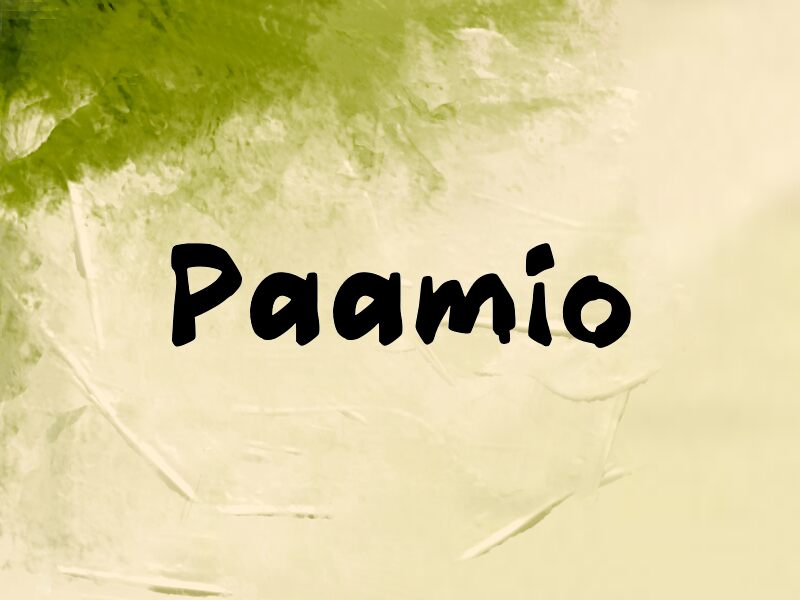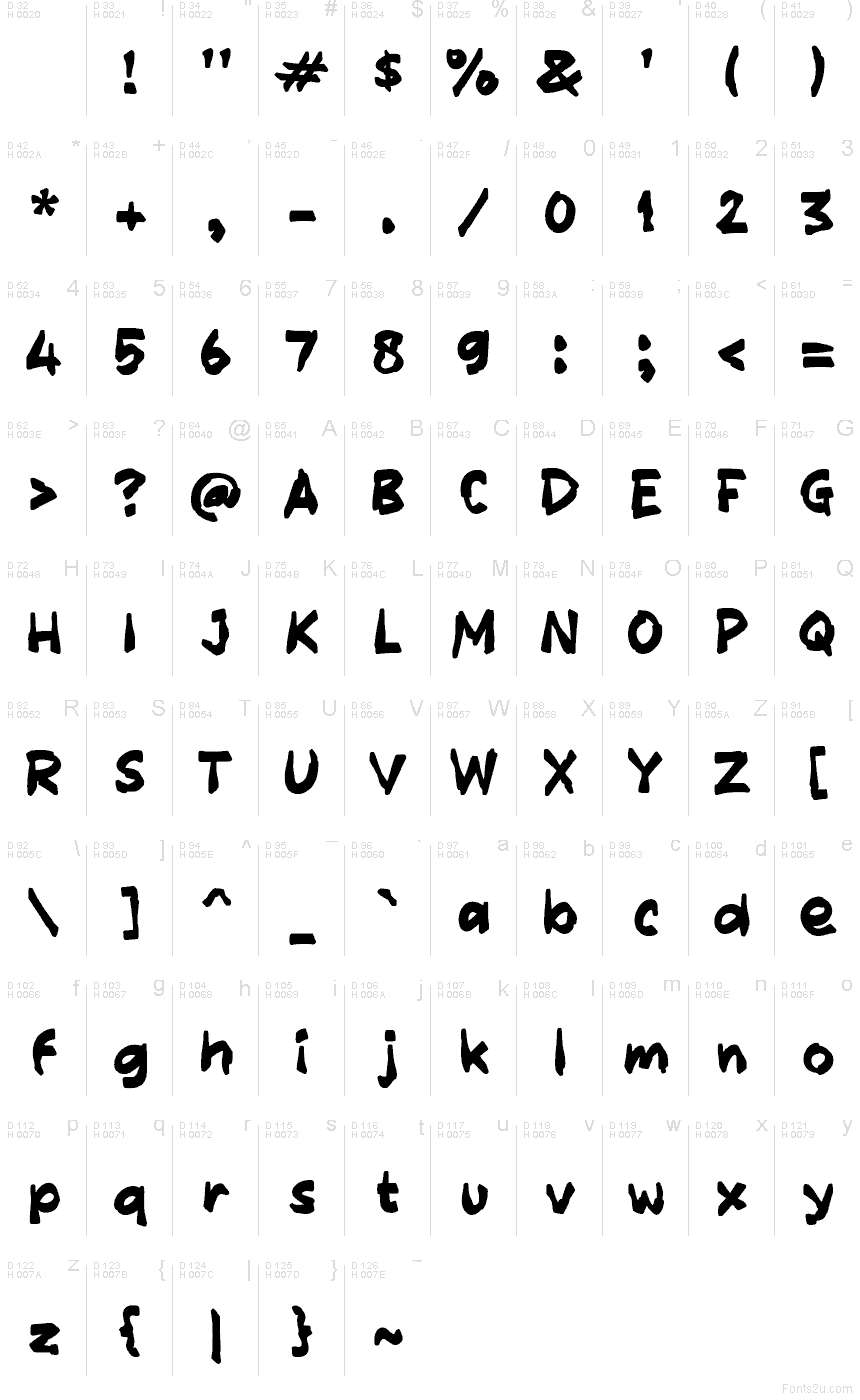
Paamio от Wep — это бесплатный кистевой шрифт с эффектным, «рукописным» характером и свободным, живым ритмом. Буквы выглядят так, будто их нарисовали широкой, насыщенной краской кистью: мягкие углы, объемные кривые и мелкие детали придают шрифту небрежный, естественный вид, лишенный излишней строгости.
Он отлично подойдет для заголовков на плакатах, брендинга кафе, обложек альбомов, упаковки и соцсетей — везде, где нужен бесплатный шрифт, передающий тепло без лишней слащавости. Благодаря жирным и плотным штрихам Paamio особенно хорошо смотрится в коротких заголовках, крупных надписях и акцентных фразах, которым не хватает той самой рукотворной выразительности.